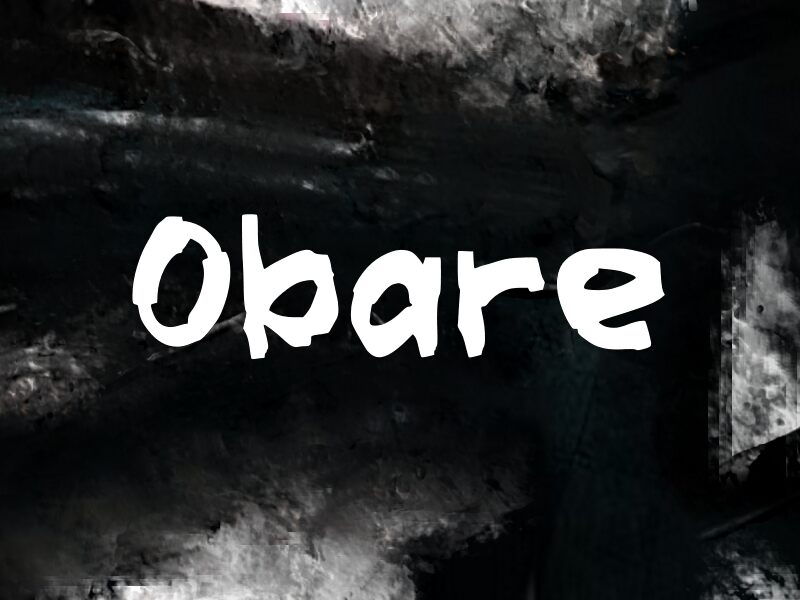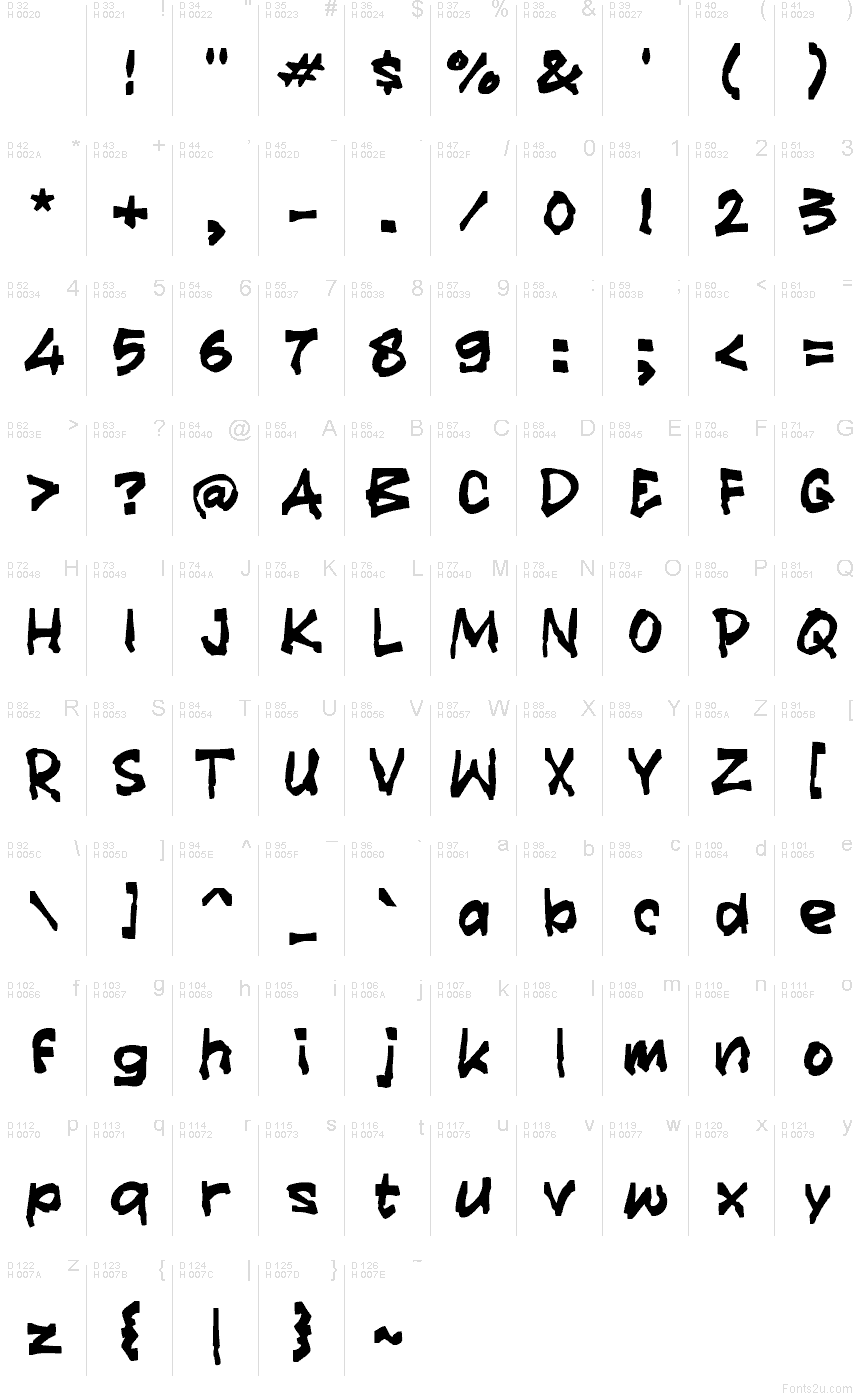
Obare
Obare de Wep es una tipografía brush gratuita definida por trazos amplios, extremos cortados y bordes irregulares que mantienen la esencia cruda de las letras. Su ritmo se siente rápido y artesanal; gracias a sus formas redondeadas y un sutil vaivén, el diseño evoca más la pintura de póster que un marcador convencional.
Esa textura áspera es ideal para flyers musicales, diseños de streetwear, portadas de fanzines, packaging y publicaciones en redes sociales donde se busca un estilo directo y hecho a mano. Los titulares cortos y los logotipos ganan mucha fuerza, ya que el ritmo enérgico del pincel aporta personalidad a cualquier frase sin depender de efectos añadidos.